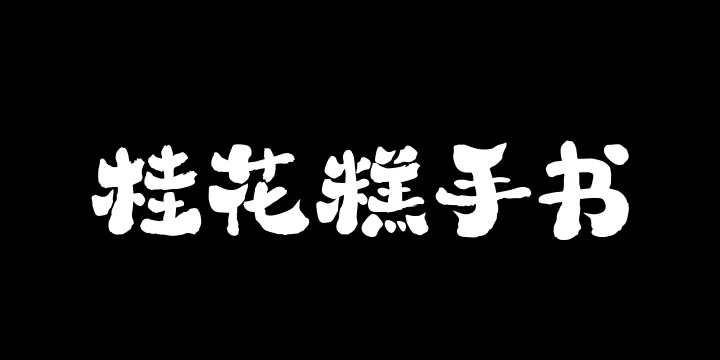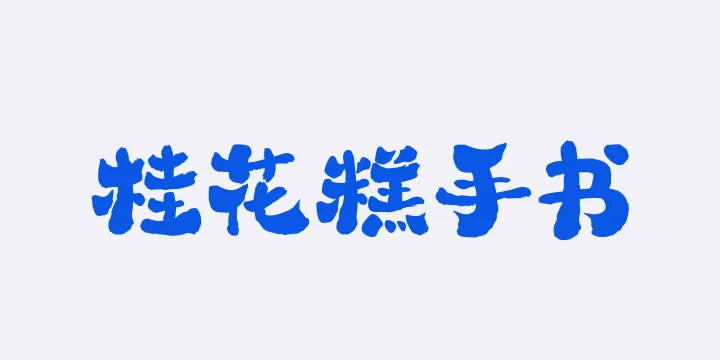
山海桂花糕手书W By 山海字库 商用字体
字体全名: 山海桂花糕手书W
字体简介: 山海桂花糕手书,是一款全新的卡通+古风毛笔字体,包含汉字9169个,符号200+个。该字体童趣可爱,结构多变灵动,字形活泼清新,造型生动有趣,具有灵活的适用性,天真俏皮又不失时尚感;同时兼具古风元素,古朴典雅,以毛笔风格的表现形式,使字体更别具一格,笔画的飞白效果使字体的气息更加流畅,笔画间的关系密不可分,同时也增加了字体的自由俏皮之感。